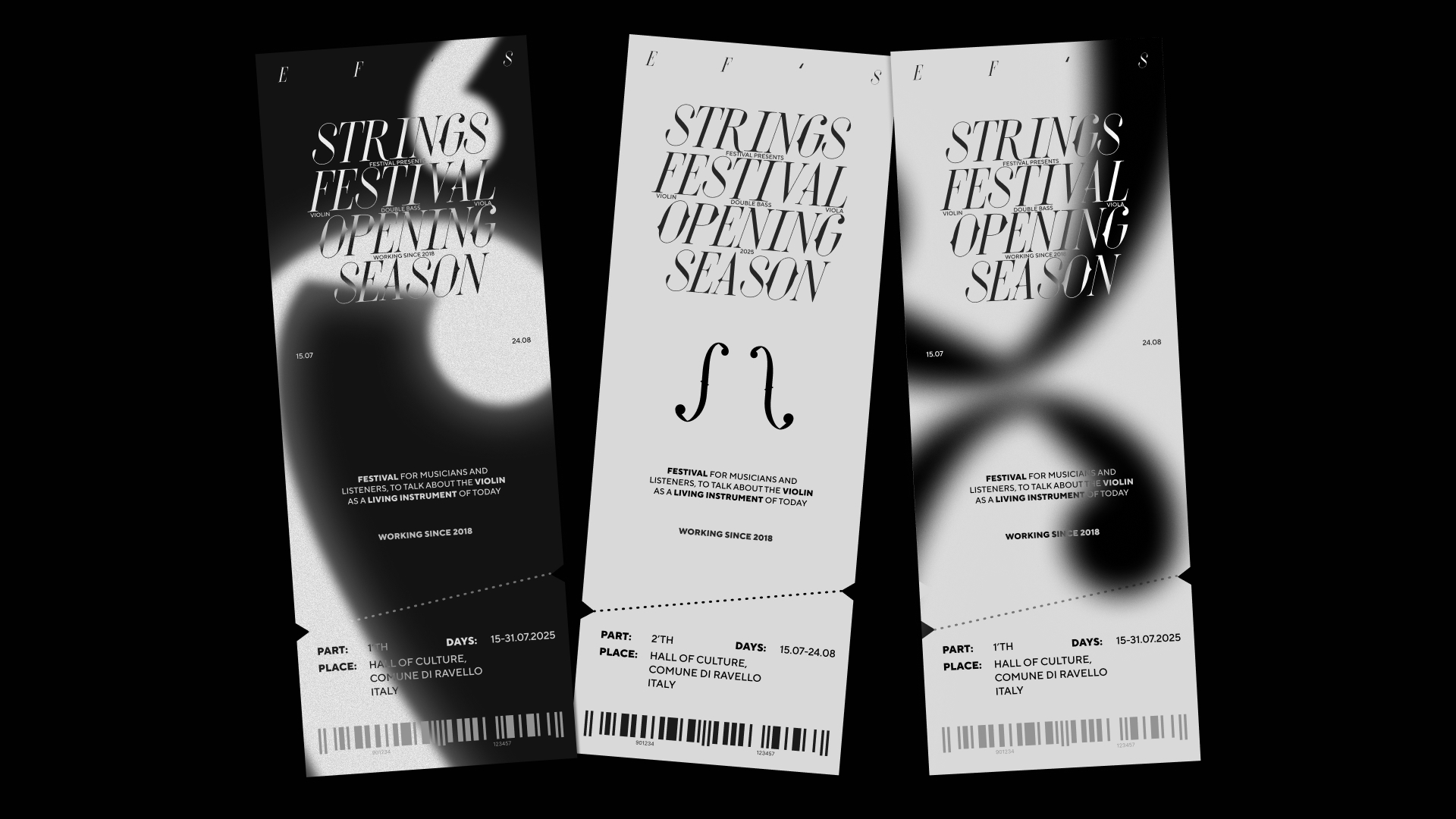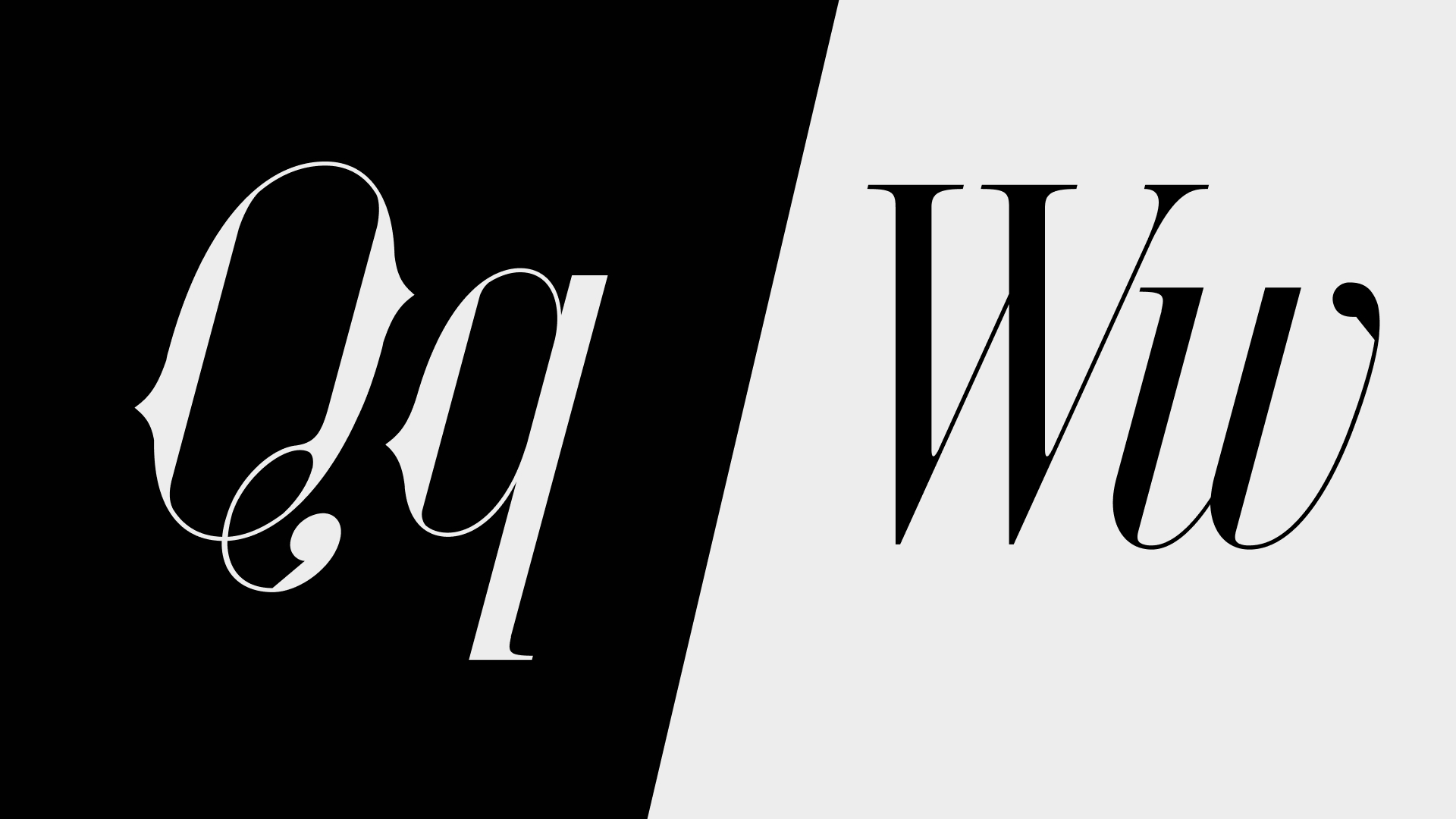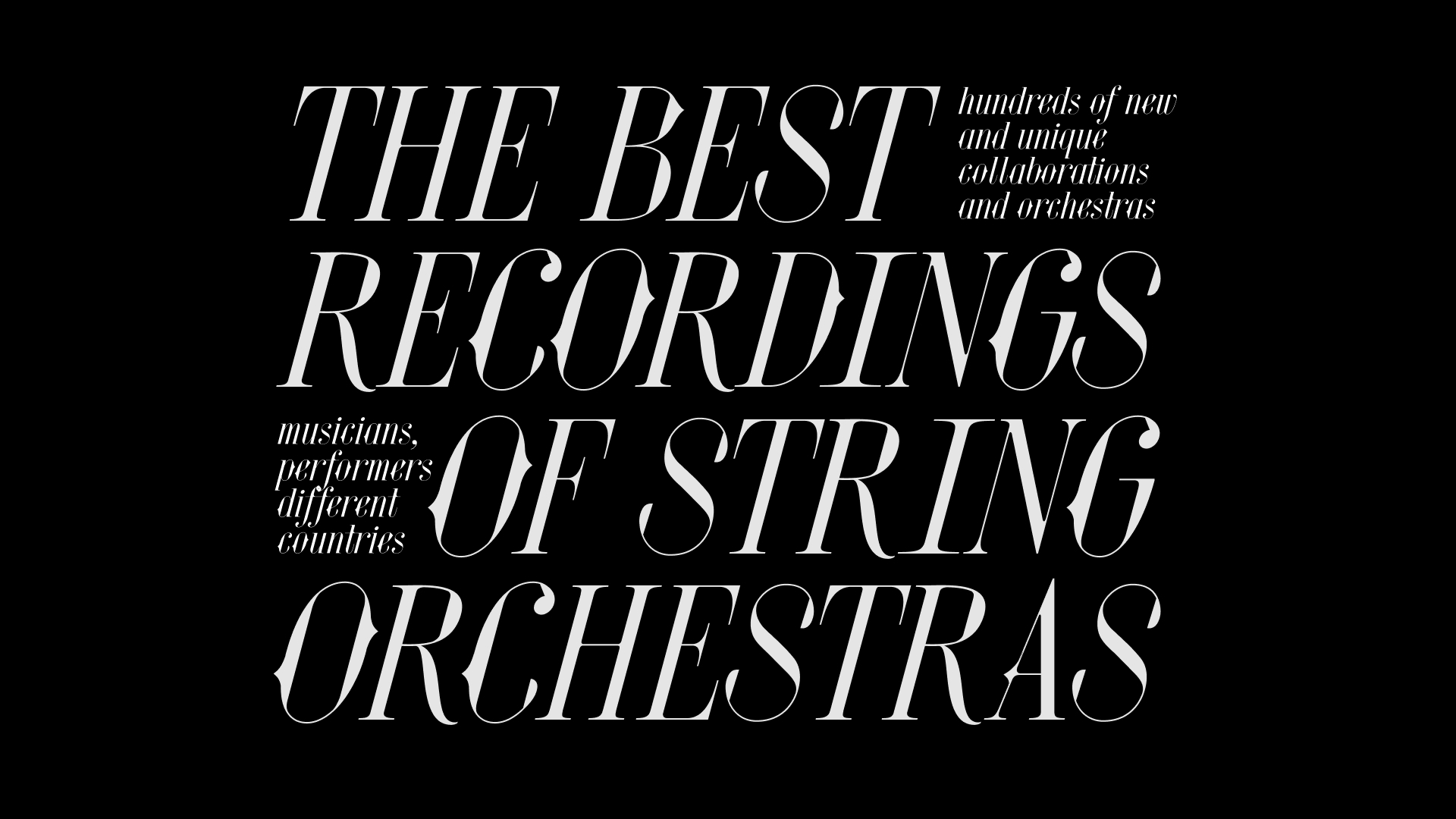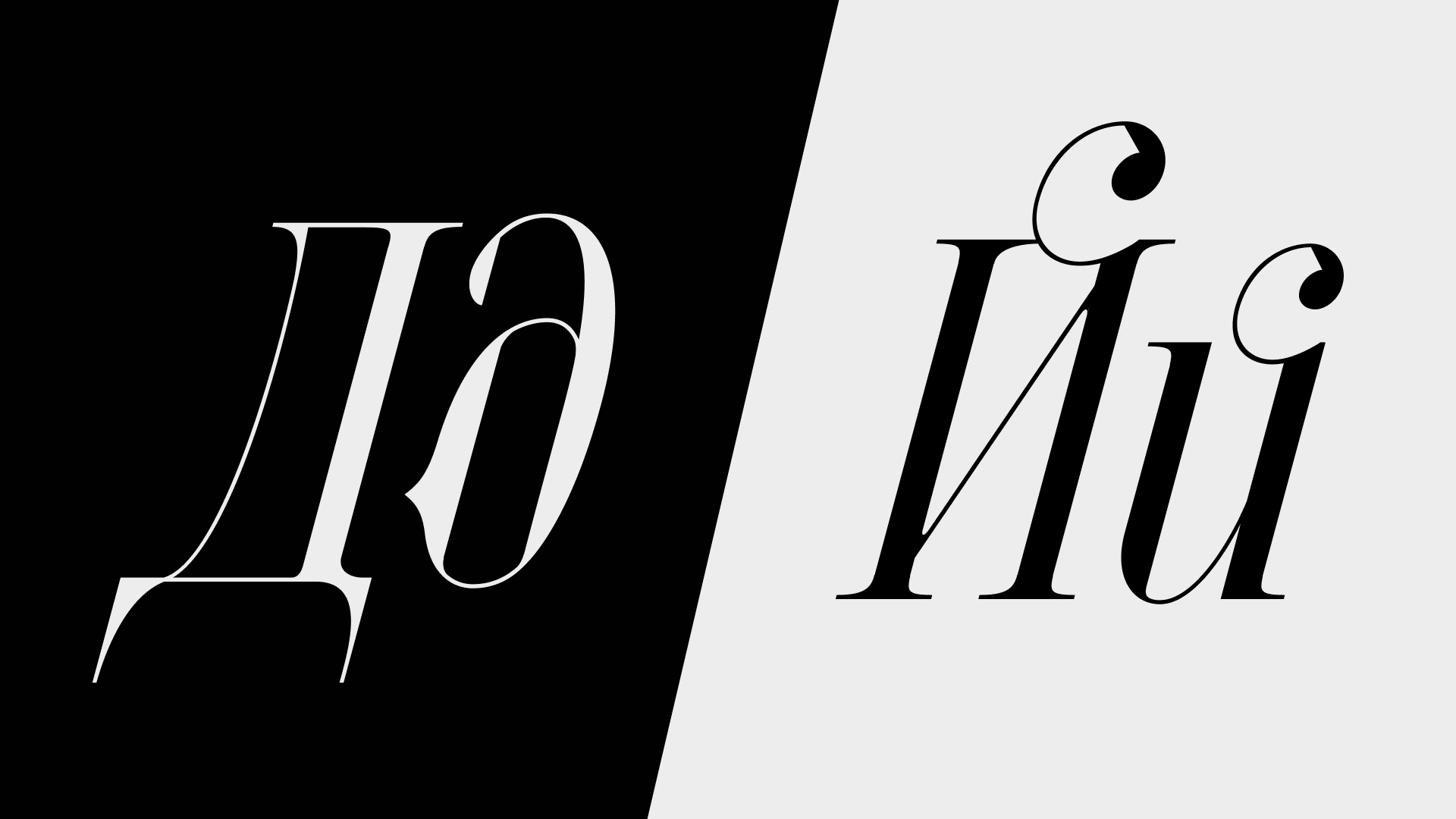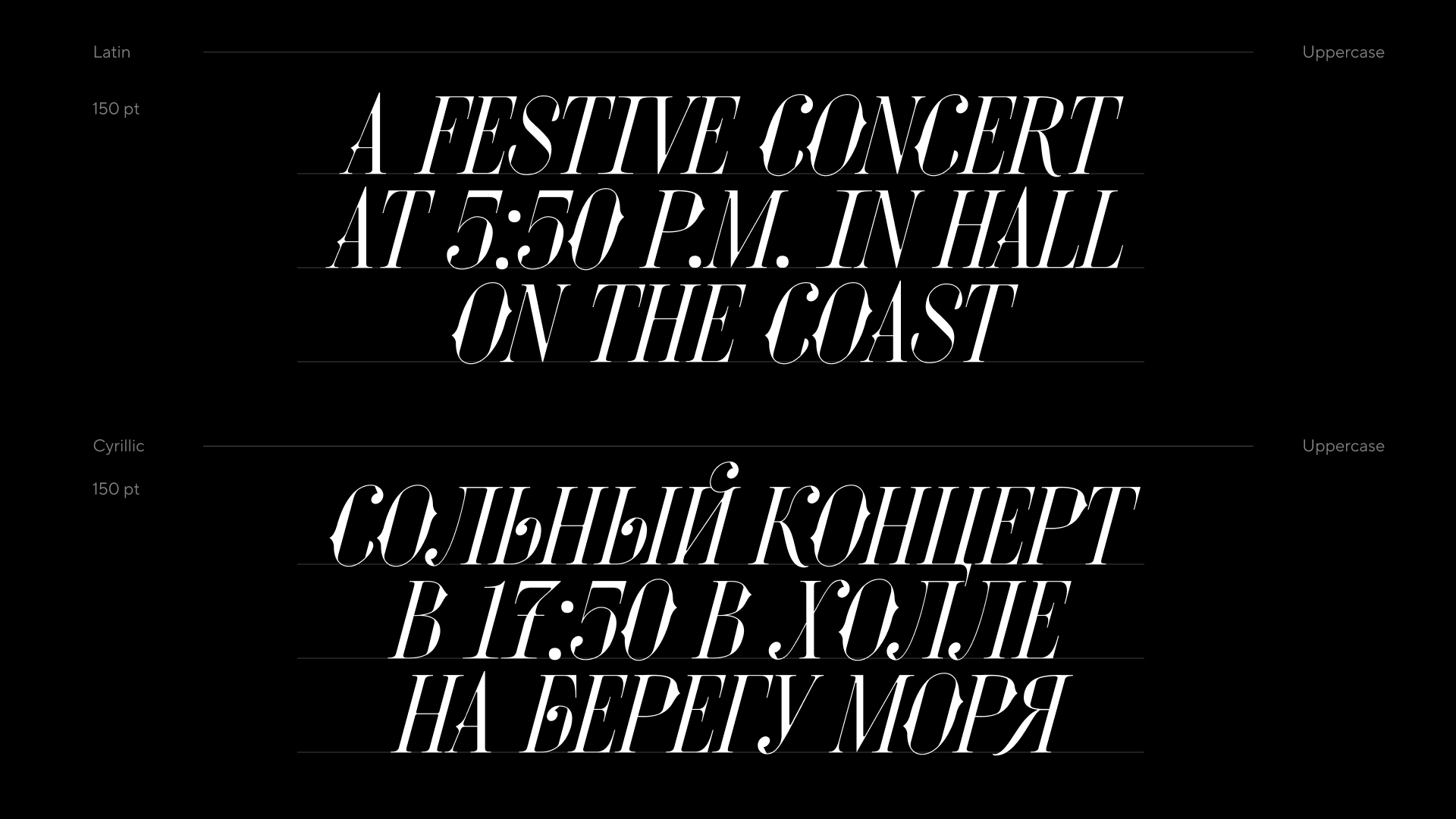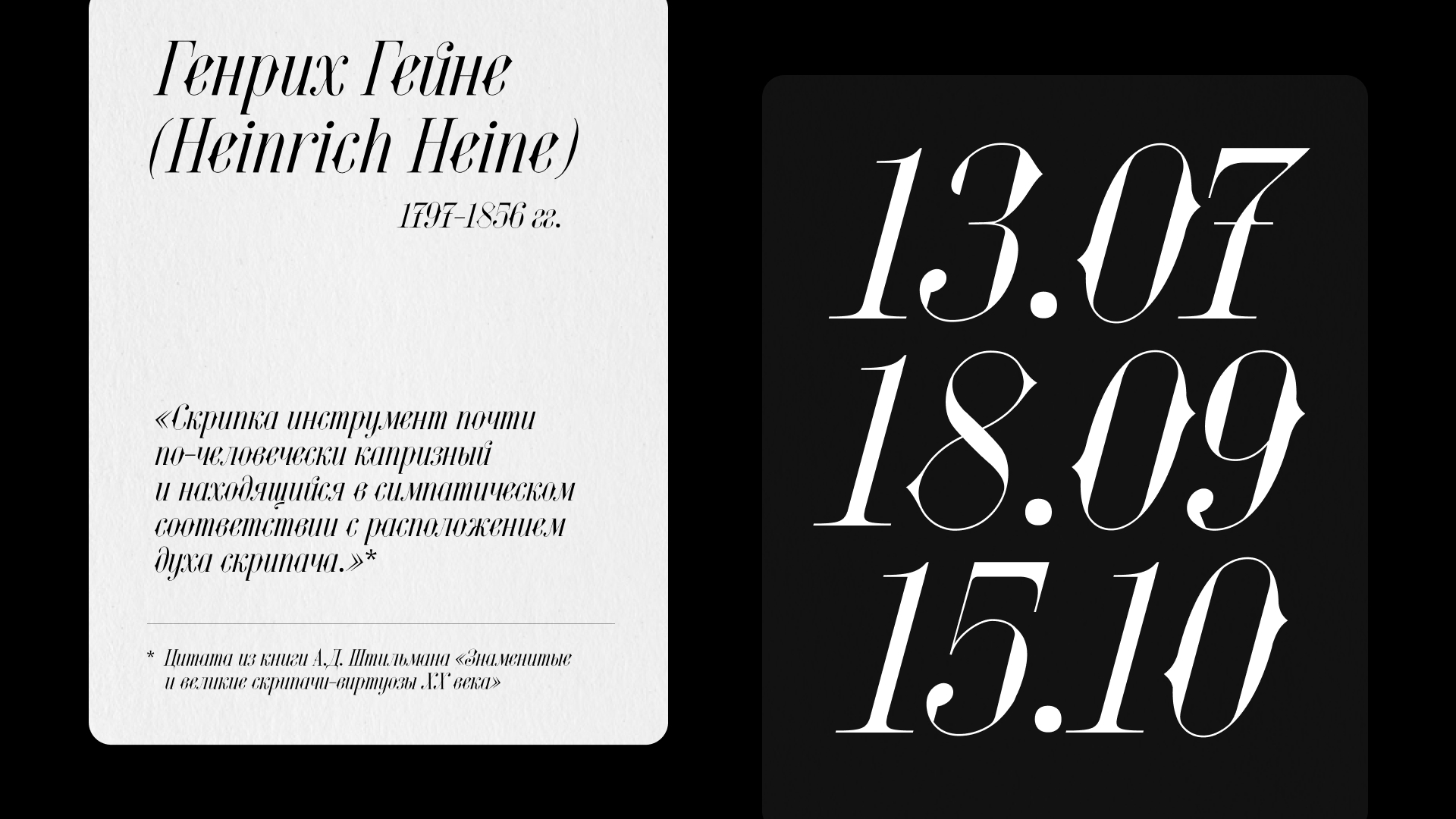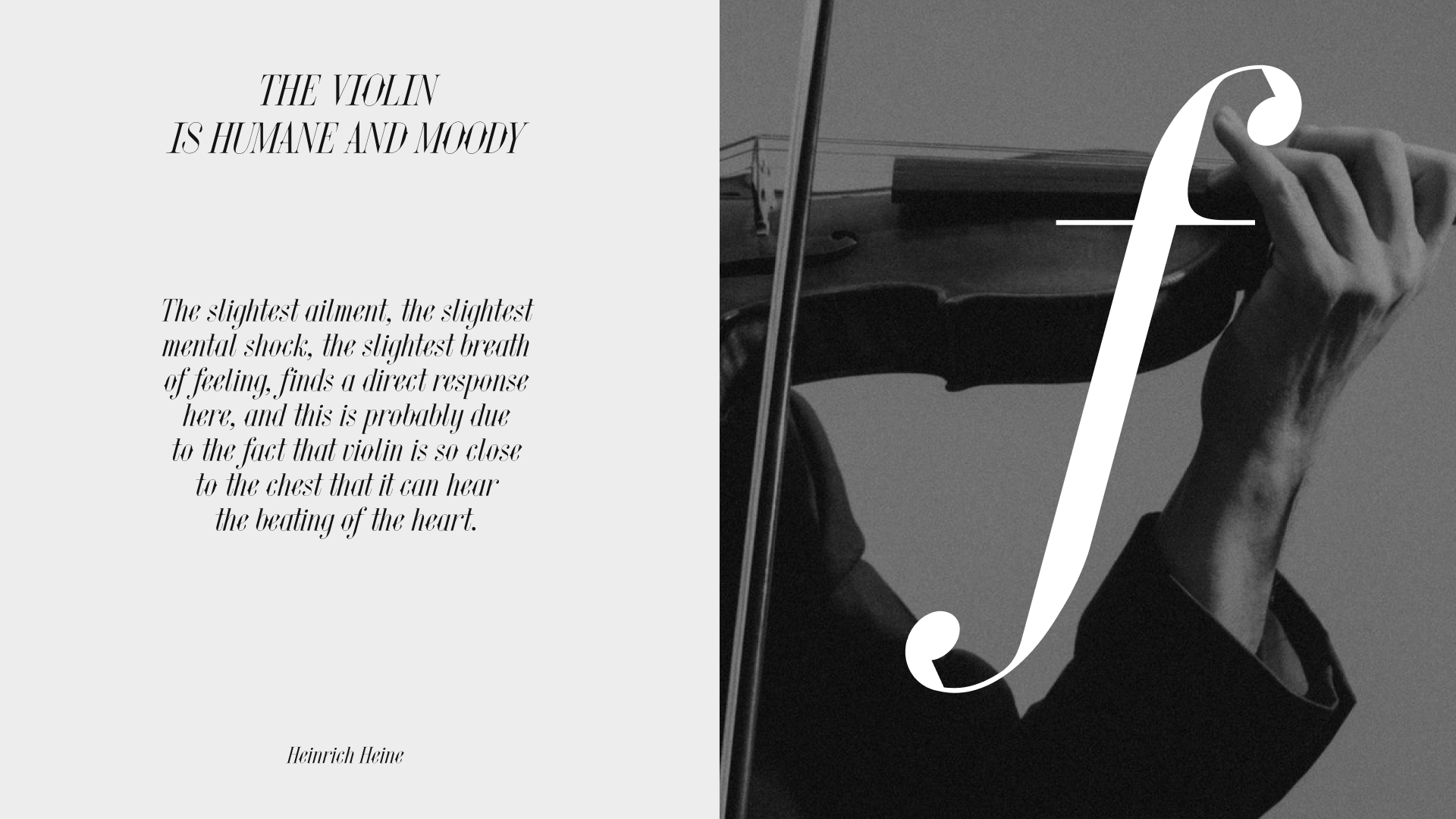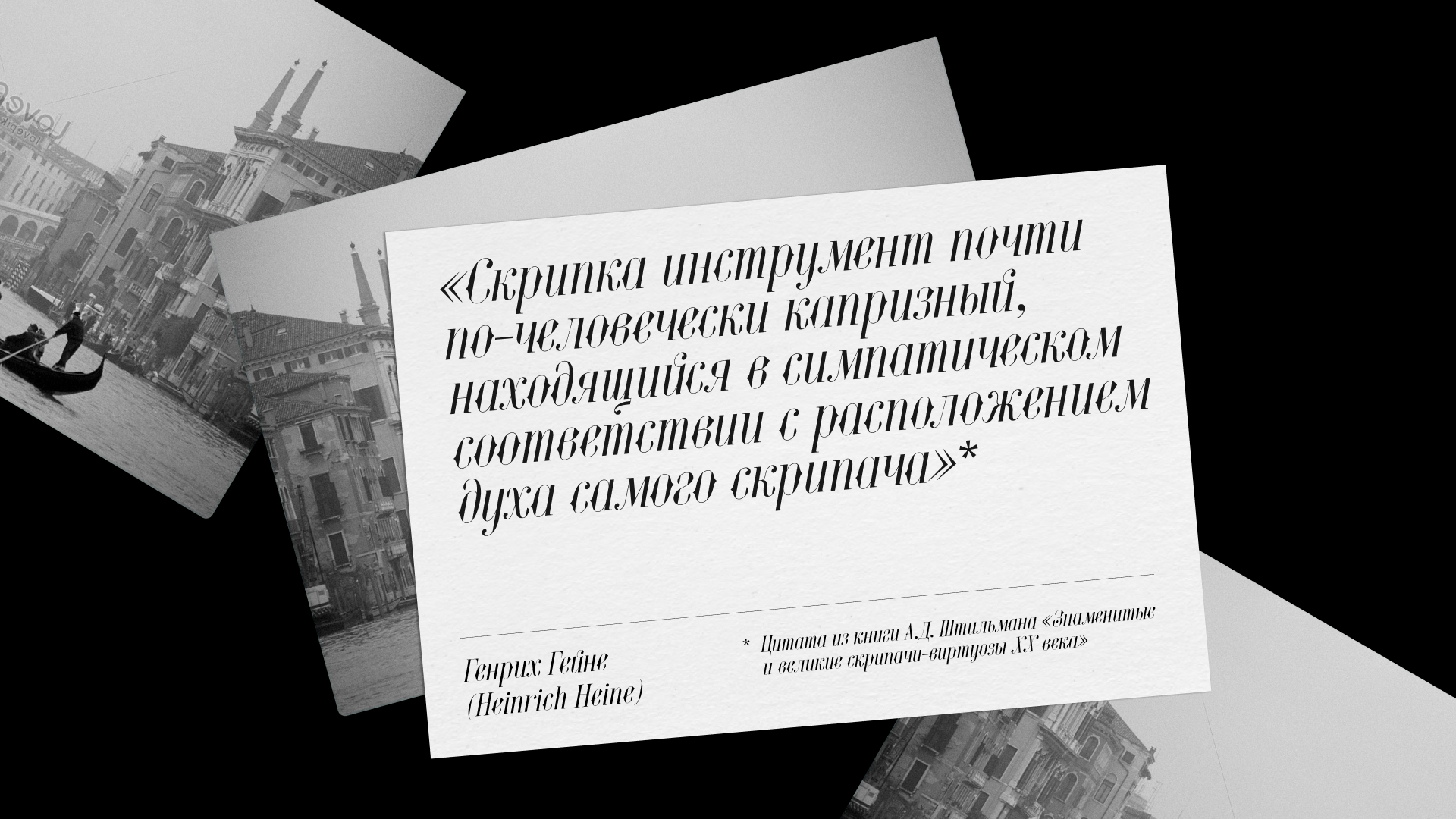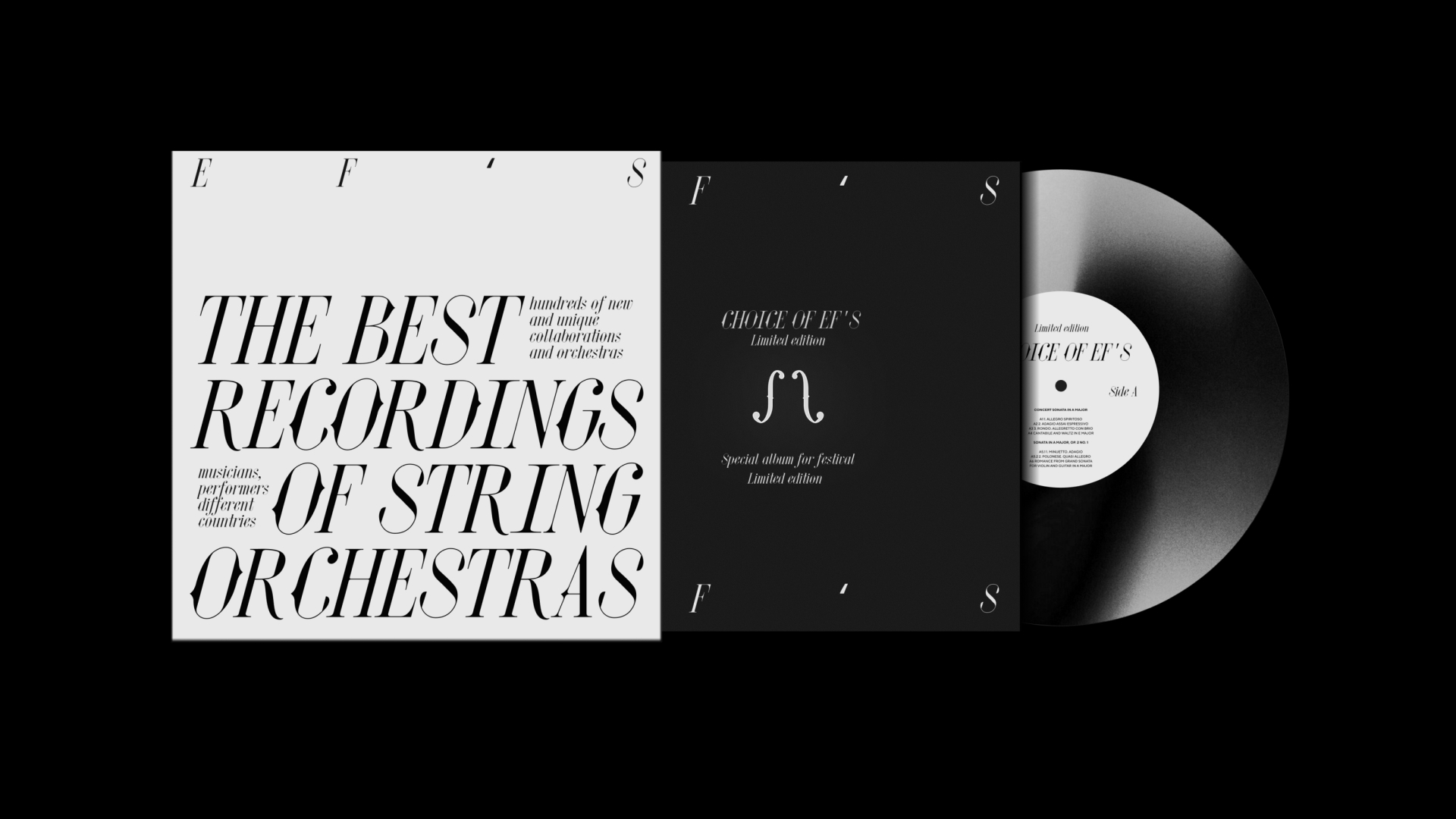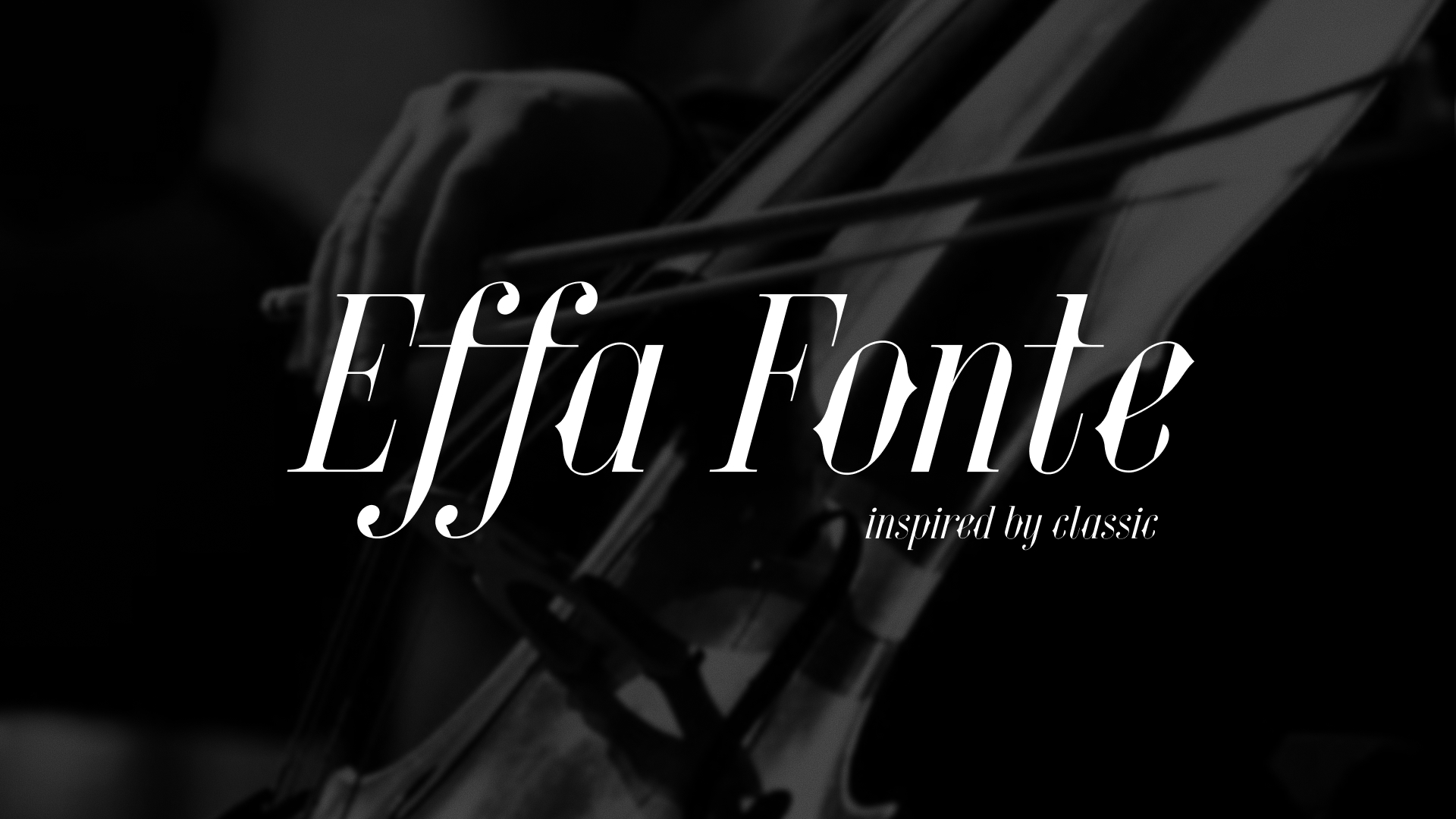
Effa Font
Effa — высококонтрастная курсивная антиква с классическим струнным музыкальным характером и утонченной грацией.
Основой для шрифта послужила форма классических эфов скрипичных струнных инструментов, которые играют роль резонатора звука: резкие скосы и врезающиеся линии в каплях эфов являются формообразующими элементами стемов и декоративных элементов, а шипы в овалах, расположенные на разных уровнях, повторяют форму острых шипов середины эфов.